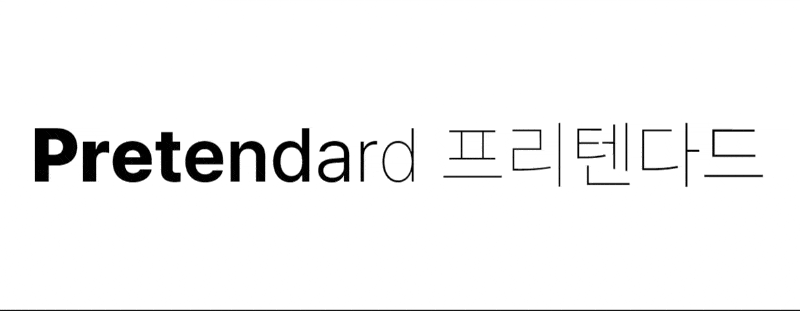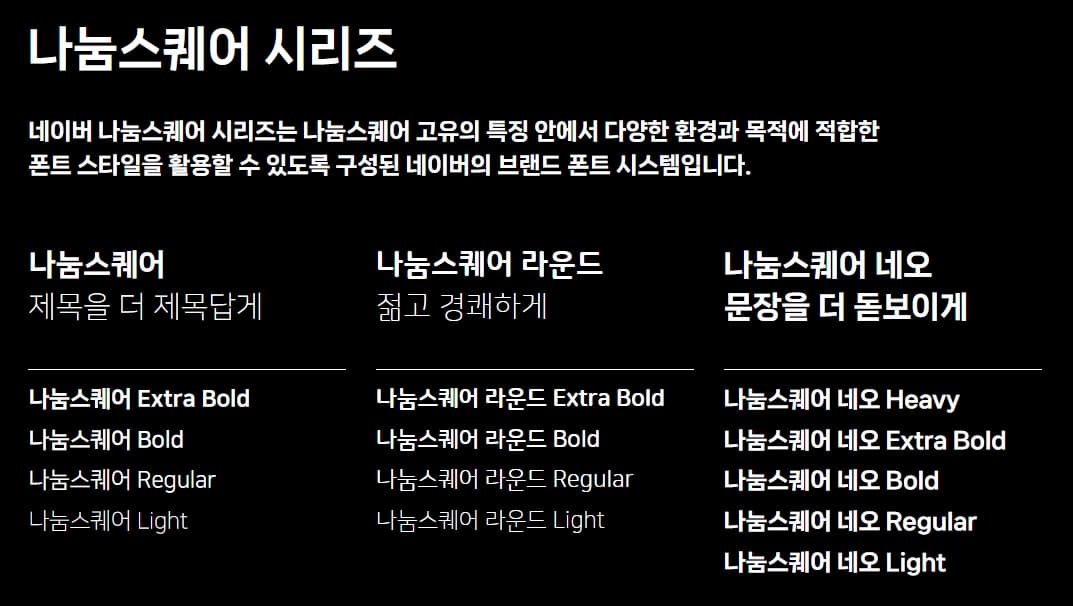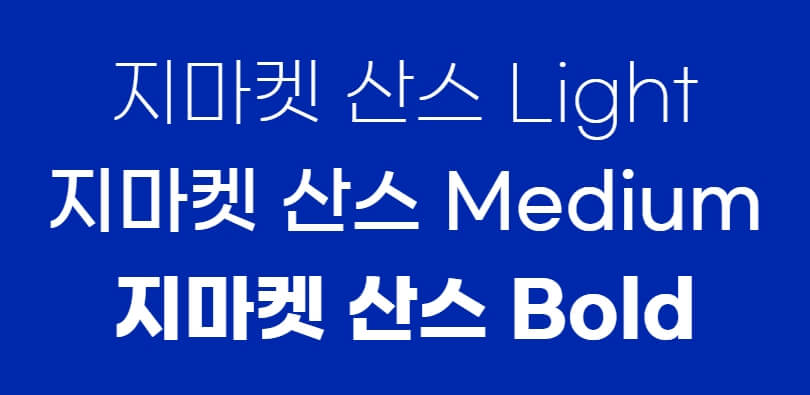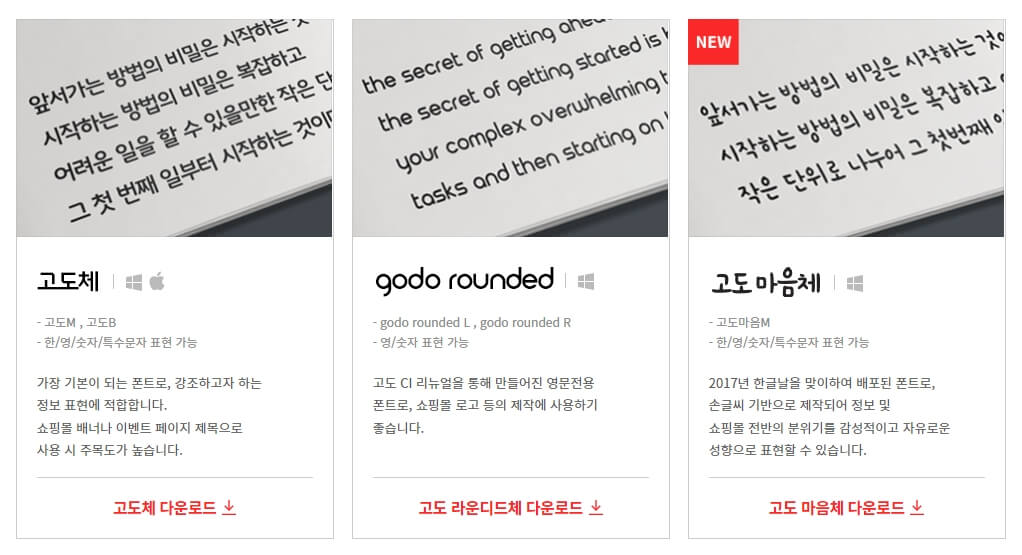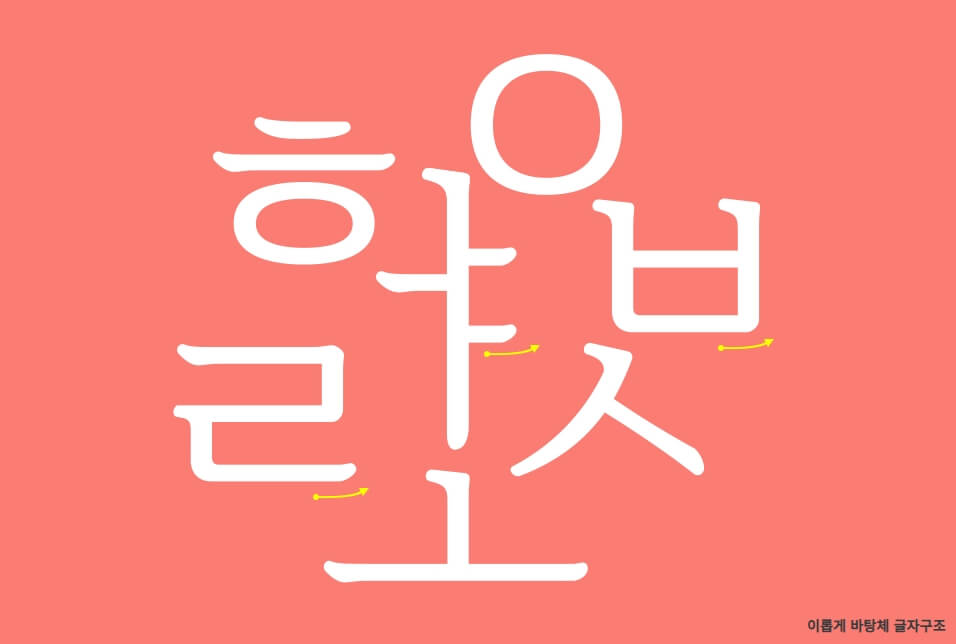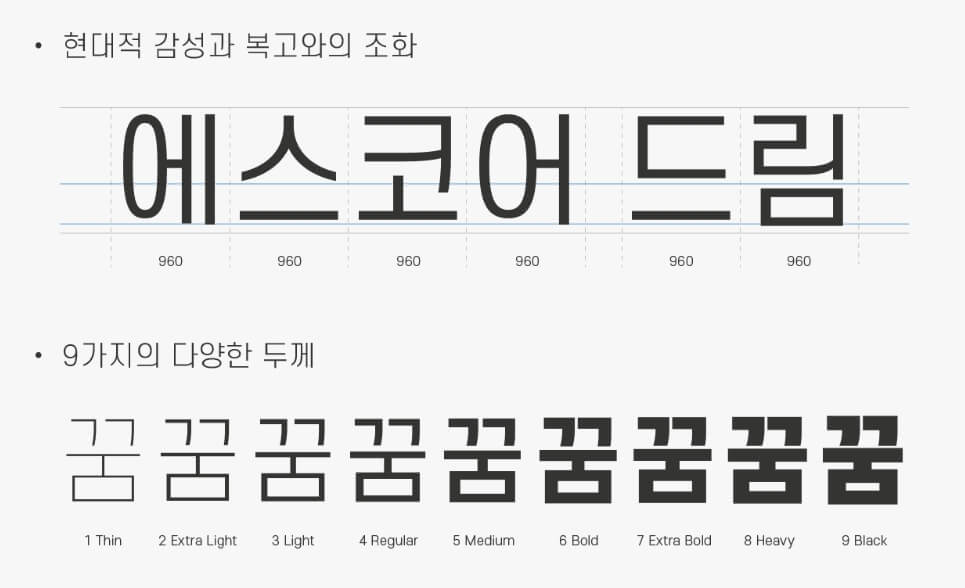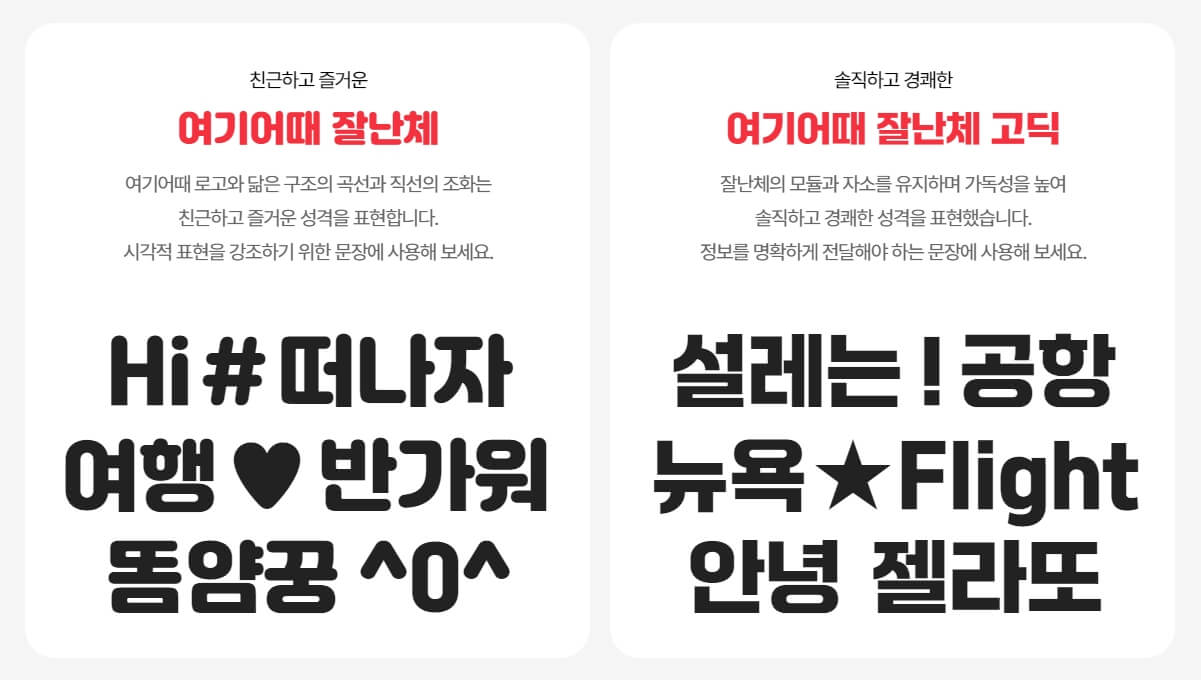
무료 한글(국문) 웹 폰트 베스트 7 & 무료 폰트 모음 사이트 베스트 5: 디자이너 필수 팁
아직도 웹사이트에 노토산스만 쓰시나요? 요즘 가독성 높고 예쁜 무료 폰트를 제공하는 곳들이 많습니다. 저만 쓰려고 모아둔 가독성도 높고 어느 웹사이트에나 잘 어울릴 만한 무료 웹 폰트 7가지 공개해 드립니다.
웹 디자인에서 폰트는 정보 전달뿐만 아니라 웹사이트의 브랜드 아이덴티티와 사용자 경험에 있어서 고려해야 할 필수 요소인 거 아시죠? 혹시 더 체계적으로 알고 싶으시다면 웹 폰트에 대해 쓴 글을 한번 읽어보세요.
본인이 좋아하는 유료 폰트 아이템을 구매하는 것도 나쁘진 않지만 많은 웹사이트를 디자인할 때 유료로 쓰기엔 너무 제한적이죠. 요즘 무료로 제공되는 퀄리티 높은 폰트들도 많이 있고요. 그래서 쓸 만한 무료 폰트 7가지를 소개해 드리려고 합니다.
무료 한글 웹 폰트 7가지
1. Pretendard(프리텐다드)
2021년에 길형진 디자이너가 애플의 산돌고딕 Neo, San Francisco 폰트를 대체하기 위해 디자인한 한국의 오픈 소스 폰트입니다. 최근 23년 11월 업데이트를 한 매우 핫한 폰트라고 할 수 있죠.
- 폰트 스타일: 고딕체, 9가지 굵기 제공 (Thin, ExtraLight, Light, Regular, Medium, SemiBold, Bold, ExtraBold, Black)
- 언어 지원: 라틴어(영어), 키릴 문자, 그리스어 등을 지원
2. 나눔스퀘어
나눔스퀘어 폰트는 네이버에서 개발한 무료 한글 폰트 시리즈로 온라인에서의 한글 표현을 높이기 위해 만들어졌으며, 다양한 용도로 사용할 수 있는 35개의 폰트로 구성되어 있습니다. 다양한 사이트에 잘 어울리기 때문에 제가 좋아하는 폰트이기도 하죠.
- 폰트 스타일: 고딕체, 4가지 굵기 제공 (Regular, Bold, Light, ExtraLight)
- 언어 지원: 한글 2,350자, 추가 문자 129자, 라틴어 94자 등 총 985자의 글리프 지원
- 기타: 시리즈로써 나눔스퀘어, 나눔스퀘어 라운드, 나눔스퀘어 네오
3. Gmarket Sans(지마켓 산스)
지마켓 산스 폰트는 G마켓 브랜드 아이덴티티를 반영하여 설계된 무료 폰트로써 다양한 브랜드, 판매자, 사용자들이 제한 없이 공유하고 사용할 수 있도록 만들어졌습니다. 첫 닿자, 홑자, 받침자로 조합 가능한 모든 한글 표현이 가능하도록 제작되었다고 해요.
- 폰트 스타일: 고딕체, 3가지 굵기 제공 (Light, Medium, Bold)
- 언어 지원: 한글 11,172자, 영문 95자, 특수문자 986자 지원
4. 고도체
고도체 폰트는 NHN Godo에서 개발한 무료 한글 폰트로써, 쇼핑몰 정보와 브랜드 이미지를 효과적으로 표현하기 위해 설계되었습니다. 고도체 폰트는 강조된 정보를 전달하는 데 적합하여 쇼핑몰 배너나 이벤트 페이지 제목으로 사용 시 주목도가 높다고 합니다.
- 폰트 스타일: 2가지 굵기 제공 (Medium, Bold)
- 기타: 시리즈로써 고도체, 고도마음체, gogo Rounded(영문, 숫자만 가능)
5. 이롭게 바탕체
이롭게 바탕체는 국내 최초 웹전용 한글 세리프 폰트로써, 온/오프라인에서 현대적인 디자인에 활용할 수 있습니다. 이 폰트는 디지털 환경에 최적화되어 있으며, 풍부한 문자 지원과 경량화 설계로 웹에서 효과적으로 사용할 수 있습니다.
- 폰트 스타일: 바탕체, 1가지 굵기 제공 (Medium)
- 언어 지원: 한글 11,172자 지원
6. 에스코어 드림 (S-Core Dream)
에스코어 드림은 국내 기업 에스코어에서 개발한 무료 한글 폰트로써, '꿈'과 '드리다'라는 두 가지 의미를 가지고 있으며, 직사각형 구조의 제목용 글꼴로 복고적인 형태에 현대적인 감성을 담았다고 합니다.
- 폰트 스타일: 9가지 굵기 제공 (Thin, Extra Light, Light, Regular, Medium,, Bold, Extra Bold, Heavy, Black)
- 언어 지원: 한글 11,172자, 영문 95자, 특수문자 986자 지원
7. 여기어때 잘난체
여기어때 잘난체는 여행 플랫폼 '여기어때'의 브랜드 아이덴티티를 반영하여 개발된 무료 한글 폰트로써, 시각적 커뮤니케이션을 강화하고자 제작되었으며, 라운드와 직선을 모두 담은 모음과 곡선으로 떨어지는 자음이 특징인 타이틀 전용 서체로 디자인되었습니다.
- 폰트 스타일: 1가지 굵기 제공
- 언어 지원: 한글 11,172자, 라틴 95자, 특수문자 967자, 딩뱃 127자 지원
- 기타: Opentype 기능을 활용하여 제작한 딩뱃 127자는 여행이 연상되는 해시태그 입력 시 이미지로 변경되어 글자와 함께 사용할 수 있는 것이 특징입니다.
여기어때 잘난체
여행의 즐거운 경험을 제공하는 여기어때의 잘난체와 고딕 서체를 무료로 사용해 보세요.
gccompany.co.kr
무료 폰트 모음 사이트
1. 구글 웹폰트
구글 웹폰트는 구글이 제공하는 무료 오픈 소스 폰트 라이브러리이며, 웹 개발자와 디자이너들이 웹사이트에 쉽게 적용할 수 있도록 다양한 폰트 옵션을 제공하기 때문에 많은 웹 디자이너들이 방문하는 사이트죠. 구글 웹폰트는 웹 표준을 준수하며, 빠른 로딩 속도와 크로스 브라우저 호환성을 자랑합니다.
- 무료 사용: 구글 웹폰트는 개인 및 상업적 용도로 무료로 사용할 수 있습니다.
- 다양한 언어 지원: 라틴어, 키릴 문자, 아랍어, 히브리어, 그리스어 등 다양한 언어를 지원합니다.
- 크로스 브라우저 호환성: 모든 주요 웹 브라우저에서 호환되어 사용할 수 있습니다.
- 빠른 로딩 속도: 구글 서버에서 제공되어 빠른 로딩 속도를 보장합니다.
- 웹 표준 준수: CSS와 HTML 표준을 준수하여 웹 접근성을 높입니다.
- 다양한 폰트 스타일: 다양한 폰트 스타일과 두께, 기울기 등을 제공합니다.
Browse Fonts - Google Fonts
Making the web more beautiful, fast, and open through great typography
fonts.google.com
2. 네이버 폰트
네이버는 2008년부터 150개 이상의 폰트를 개발하고 무료로 배포하고 있는데, 특히 '나눔' 폰트 시리즈는 온라인에서의 한국어 표현을 높이고자 만든 35개의 폰트입니다. 또한 디지털 화면에 최적화된 '마루 버리' 폰트는 6만 명 이상의 사용자 의견을 반영하여 4년간 개발되었습니다. 개인의 필기체와 네이버 Clova AI 기술이 협업하여 만든 '나눔 손글씨' 폰트는 109개의 다양한 폰트를 제공합니다. 무엇보다 깔끔한 서체들을 제공하기 때문에 활용도가 높은 것 같아요.
- 무료 제공: 네이버는 개인 및 상업적 용도로 무료로 폰트를 제공하고 있습니다.
- 다양한 폰트 시리즈: '나눔', '마루 버리', '나눔 손글씨' 등 다양한 폰트 시리즈를 제공합니다.
- 한글 표현 향상: 온라인에서의 한국어 표현을 높이기 위해 개발되었습니다.
- 사용자 의견 반영: '마루 버리' 폰트는 6만 명 이상의 사용자 의견을 반영하여 개발되었습니다.
- AI 기술 활용: '나눔 손글씨' 폰트는 개인의 필기체와 네이버 Clova AI 기술이 협업하여 만들어졌습니다.
네이버 글꼴 모음
네이버가 만든 150여종의 글꼴을 한번에 만나보세요
hangeul.naver.com
3. 눈누
눈누는 상업적으로 이용할 수 있는 무료 한글 폰트를 모아 소개하는 웹사이트로써, 무료로 사용 가능 한 폰트가 많고 글꼴의 모양에 따라 필터링하여 검색할 수 있습니다. 또한 라이선스에 따라 상업적으로 사용 가능한 폰트를 제공하고 웹 폰트를 제공하기 때문에 아주 유용하게 쓸 수 있어요.
- 무료 상업용 폰트 제공: 눈누는 상업적으로 이용할 수 있는 무료 한글 폰트를 제공합니다.
- 다양한 폰트 스타일: 다양한 스타일의 폰트를 모아 소개하고 있습니다.
- 편리한 검색 기능: 글꼴의 모양에 따라 폰트를 필터링하여 검색할 수 있습니다.
- 사이트 개편: 2021년에 사이트를 개편하여 디자인을 변경하고 자주 묻는 질문 페이지와 추천 폰트 페이지에 버튼을 추가했습니다.
눈누
상업용 무료한글폰트 사이트
noonnu.cc
4. 공유마당 무료폰트
공유마당은 대한민국 문화체육관광부가 운영하는 저작권 공유 플랫으로, 다양한 무료 폰트를 제공하고 있습니다. 많은 서체들이 있는 사이트이기 때문에 온라인 문서, PPT 작성, 인쇄, 공유 등에 활용할 수 있을 것 같아요.
- 다양한 폰트 제공: 공유마당에서는 다양한 스타일의 무료 폰트를 제공하고 있습니다.
- 상업적 이용 가능: 대부분의 폰트는 상업적 및 비상업적 용도로 사용할 수 있습니다.
5. 지역별 서체
지역별 서체는 각 지역의 고유한 문화와 정체성을 반영한 폰트로써, 전국 각지의 지자체와 기관에서 지역 특색을 담은 무료 서체를 개발하여 제공하고 있습니다. 방문해 보시면 디자인할 때 알맞게 쓸 수 있는 서체들이 꽤 되니 적극 활용하시면 좋을 것 같아요.
- 지역 문화 반영: 각 지역의 고유한 문화와 정체성이 반영된 폰트를 제공합니다.
- 무료 배포: 지자체와 기관에서 개발한 서체를 무료로 배포하고 있습니다.
- 다양한 활용도: 인쇄, 출판, 웹, 모바일 등 다양한 용도로 활용할 수 있습니다.